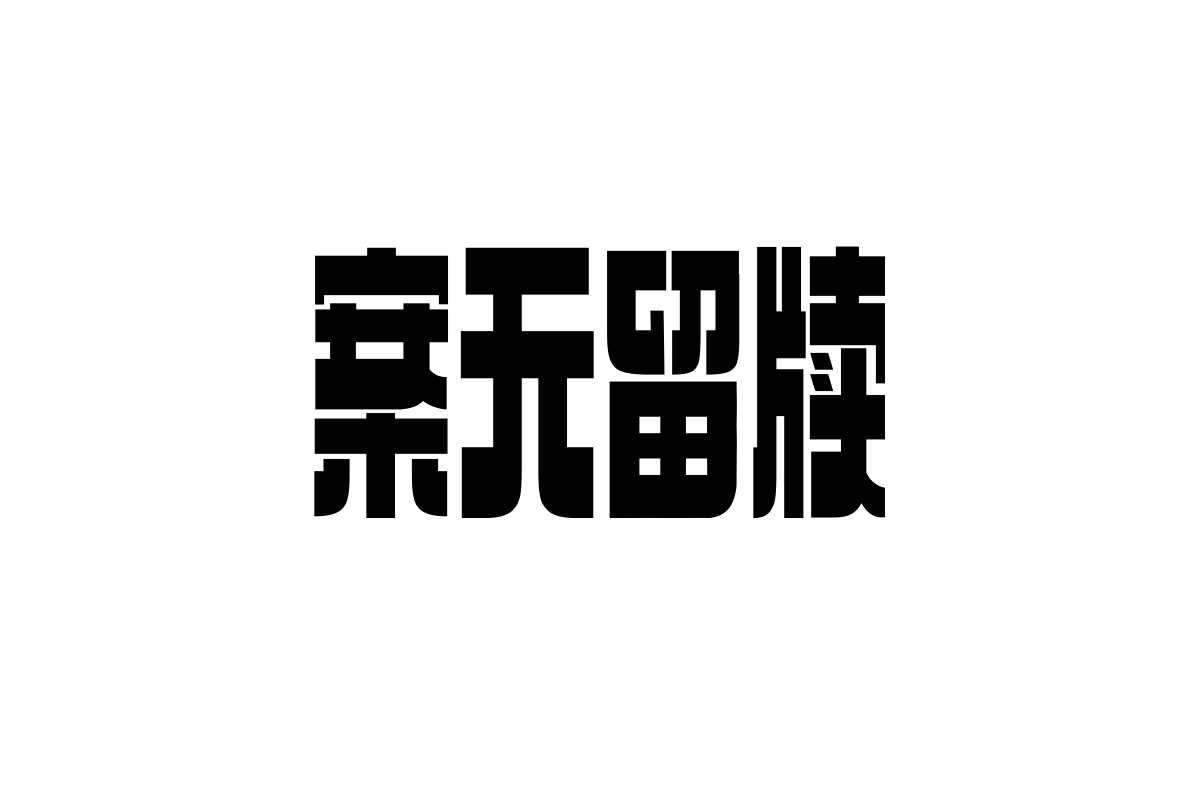
上首朋克体是一种具有独特风格和特色的字体,它以其独特的结构和设计而闻名。这种字体的特点是其笔画粗犷、线条流畅,给人一种强烈的视觉冲击感。它的每个字母都充满了力量和个性,仿佛在向世界宣告自己的存在。
上首朋克体采用了一种类似于摇滚乐的字体风格,使得整个字体看起来更加动感和有活力。它的每个字母都像是在跳动着,给人一种充满活力的感觉。这种字体非常适合用于需要表达强烈情感和态度的场合,如广告、海报、社交媒体等。
总的来说,上首朋克体是一种非常独特和引人注目的字体,它的设计和风格让人无法忽视。无论是用于商业还是艺术领域,它都能给人留下深刻的印象。